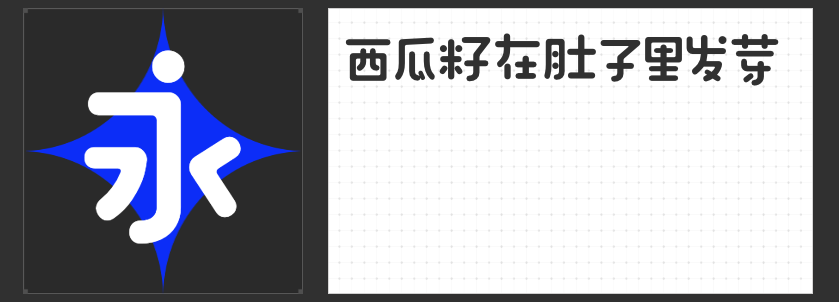
能为Logo设计注入灵魂与个性的四款字体!大力推荐
在Logo设计中,字体的选择是塑造品牌形象的关键一步。一款合适的字体不仅能够传递品牌的核心理念,还能让Logo在视觉上更具吸引力和辨识度。为大家推荐四款适用于Logo设计的独特字体,它们风格各异,能够满足不同品牌的设计需求。
1. 造字侠侠义简繁
造字侠侠义简繁是一款极具中国传统文化韵味的字体,其设计潇洒狂放,大气磅礴,同时又不失端正平稳。这款字体的特点在于用圆转的笔画代替方折的笔画,点画之间通过勾、挑、牵丝加强呼应,整体呈现出一种流动的美感。它非常适合用于文化类品牌、传统手工艺品或具有东方美学风格的Logo设计,能够为品牌注入一份独特的文化底蕴和艺术气息。
2. 励字钧线黑简 微黑
励字钧线黑简 微黑是一款极具现代感的黑体字体,其设计以全直线为主,摒弃了过度的装饰,强调简洁与个性。字体的斜度和转折设计利落流畅,棱角分明,给人一种锐利而坚定的视觉感受。这款字体非常适合用于科技类、运动类或时尚类品牌的Logo设计,能够传递出品牌的创新精神和力量感,同时为Logo增添一份独特的现代美学。
3. 励字造桃气圆 准粗
励字造桃气圆 准粗是一款以手写感为基础的圆体字体,其设计圆润饱满,舒展流畅。字型上松下紧,重心略低,结构松弛灵活,变化多样。折笔处内外圆角兼备,部分笔画用圆形元素代替,整体风格轻快且富有活力。这款字体非常适合用于儿童品牌、食品品牌或生活方式类品牌的Logo设计,能够传递出品牌的温暖、亲和力和轻松愉悦的氛围。
4. 小豆岛默陌枝桠简
小豆岛默陌枝桠简是一款极具艺术感的字体,其设计灵感来源于传统书法的写意风格。字体疏密有致,挥洒轻重缓急,通过运笔节奏塑造线条粗细和节点,呈现出一种枯枝藤蔓的造型感。这款字体非常适合用于艺术类、文创类或自然风格品牌的Logo设计,能够为品牌注入一份独特的自然气息和艺术张力,让Logo更具辨识度和故事感。
以上四款字体各具特色,都能为你的Logo设计注入独特的灵魂与个性。根据品牌调性和设计需求,选择一款合适的字体,让你的Logo在众多品牌中脱颖而出吧!